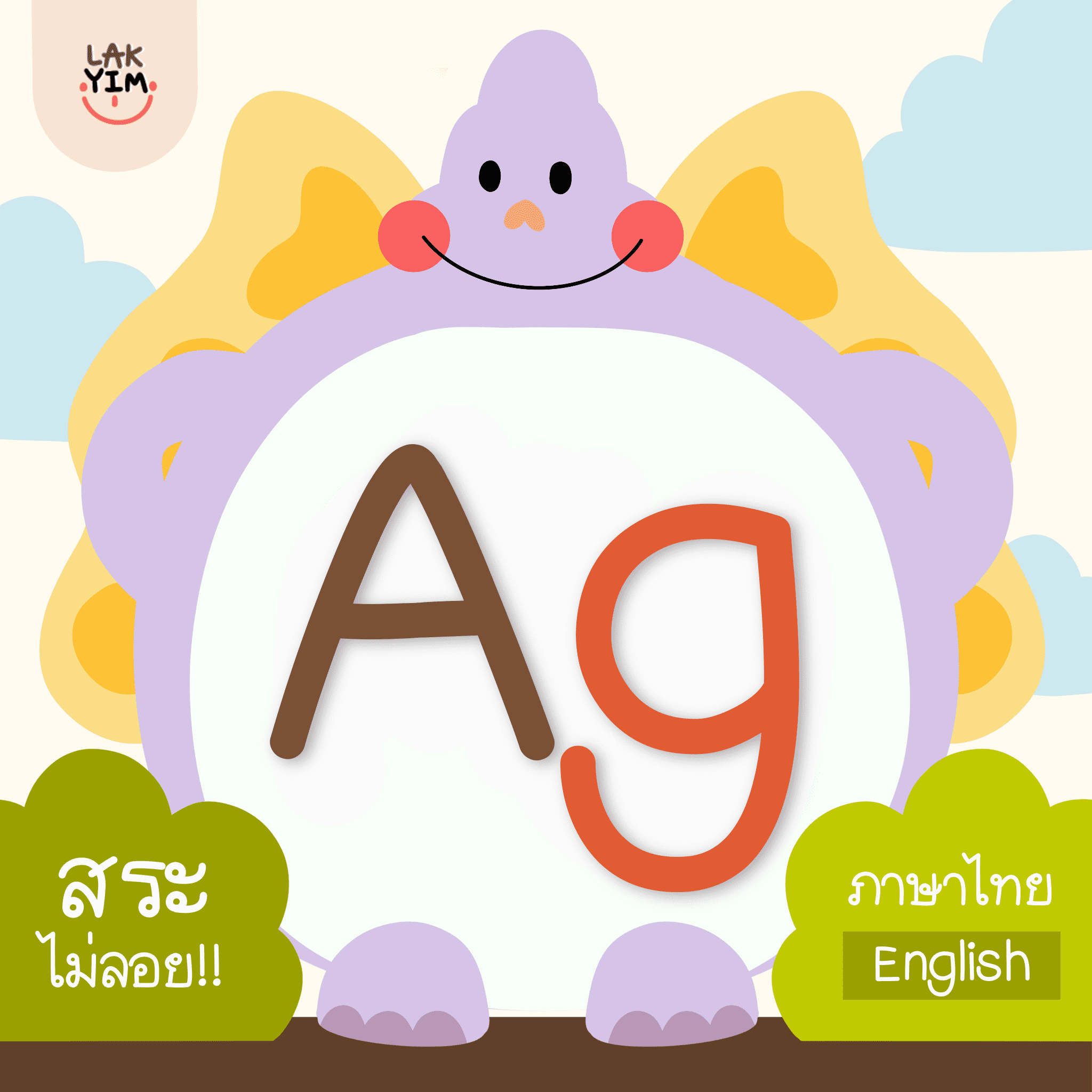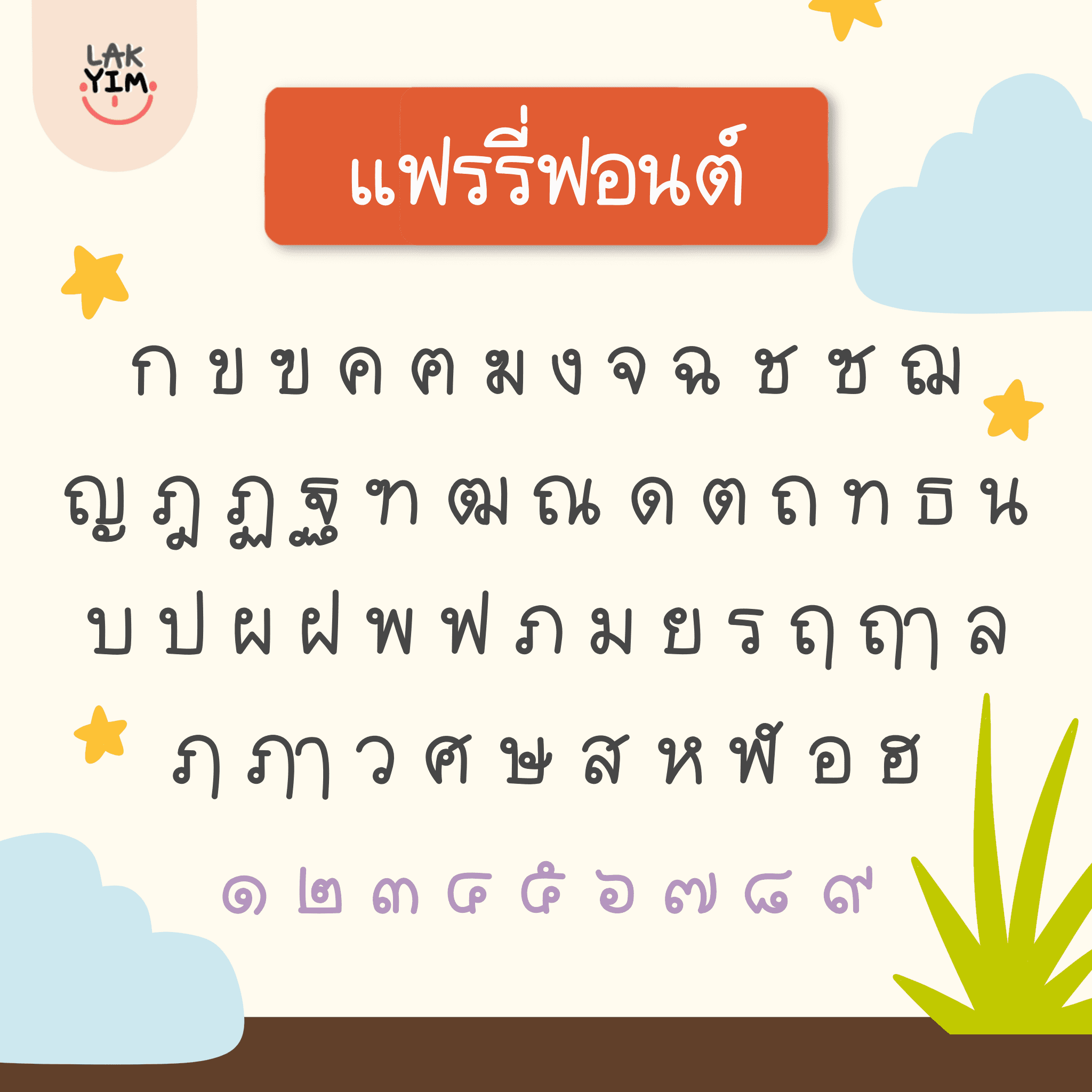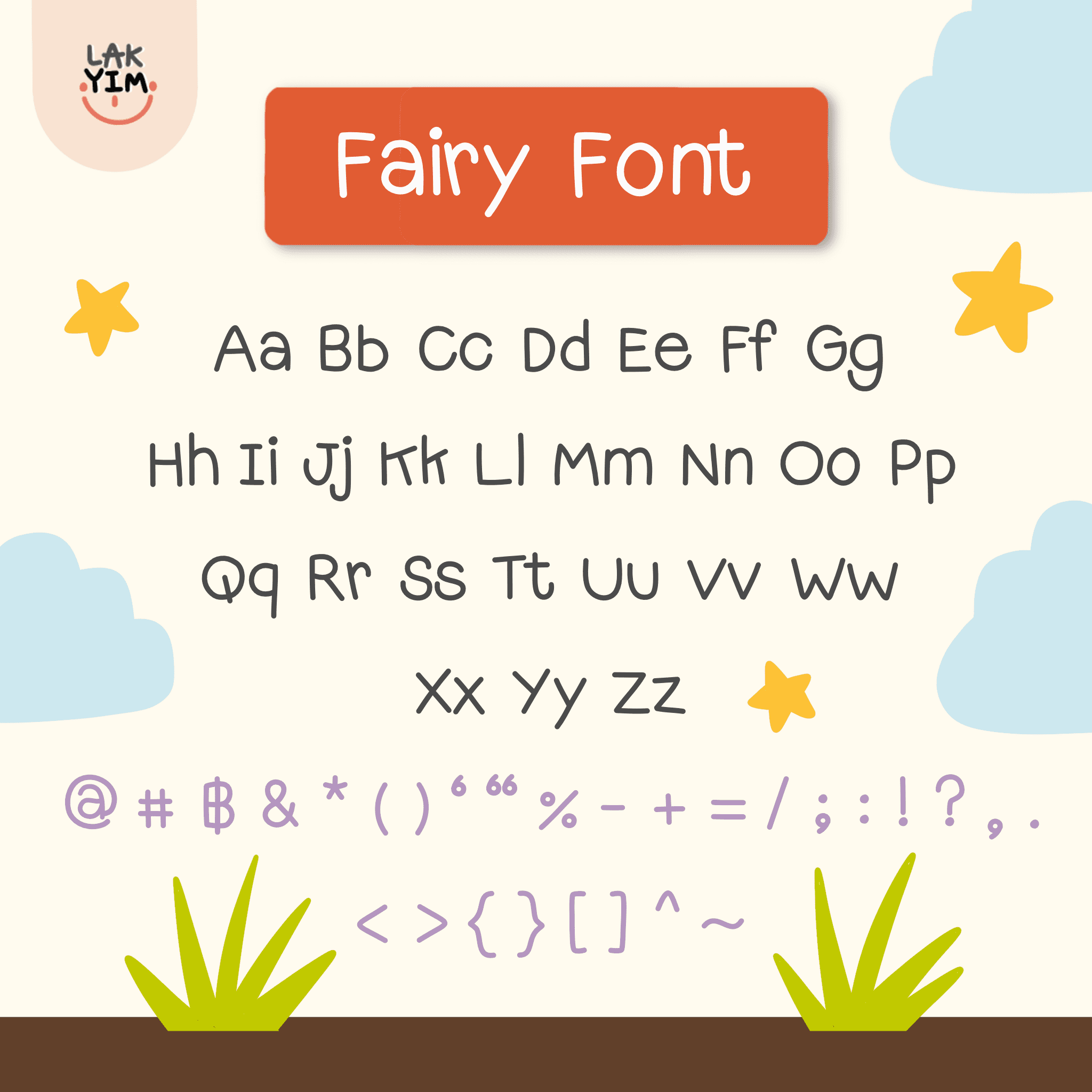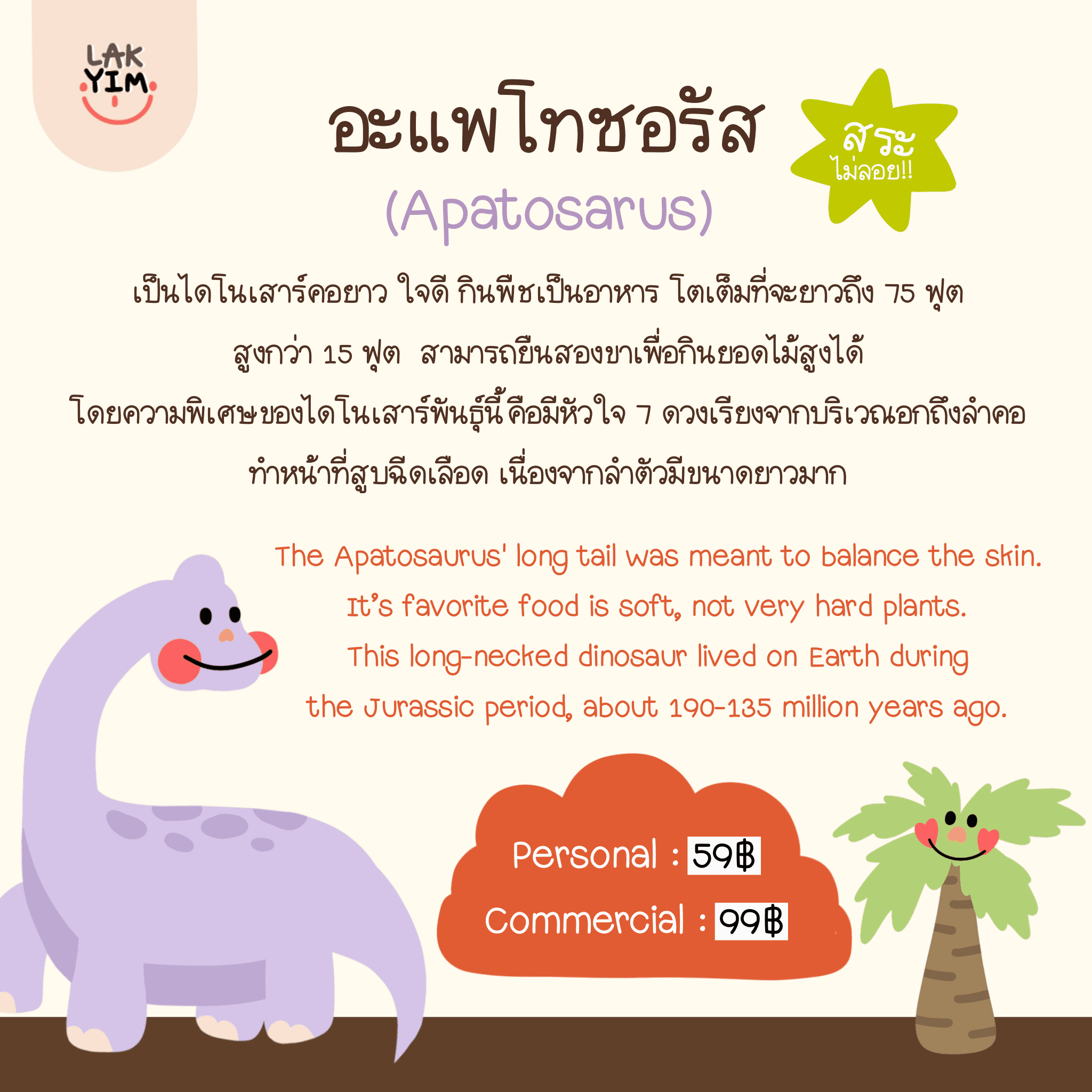
รักยิ้มมาขายฟอนต์ : FAIRY FONT
ฟอนต์ลายมือที่เป๊ะเหมือนพิมพ์ แต่ยังมีความเหมือนเขียนอยู่
– ใช้ได้กับงานทุกแบบ ไม่ว่าจะเป็นจดสรุป ตกแต่งงานต่างๆ
– มีทั้งภาษาไทยและภาษาอังกฤษ